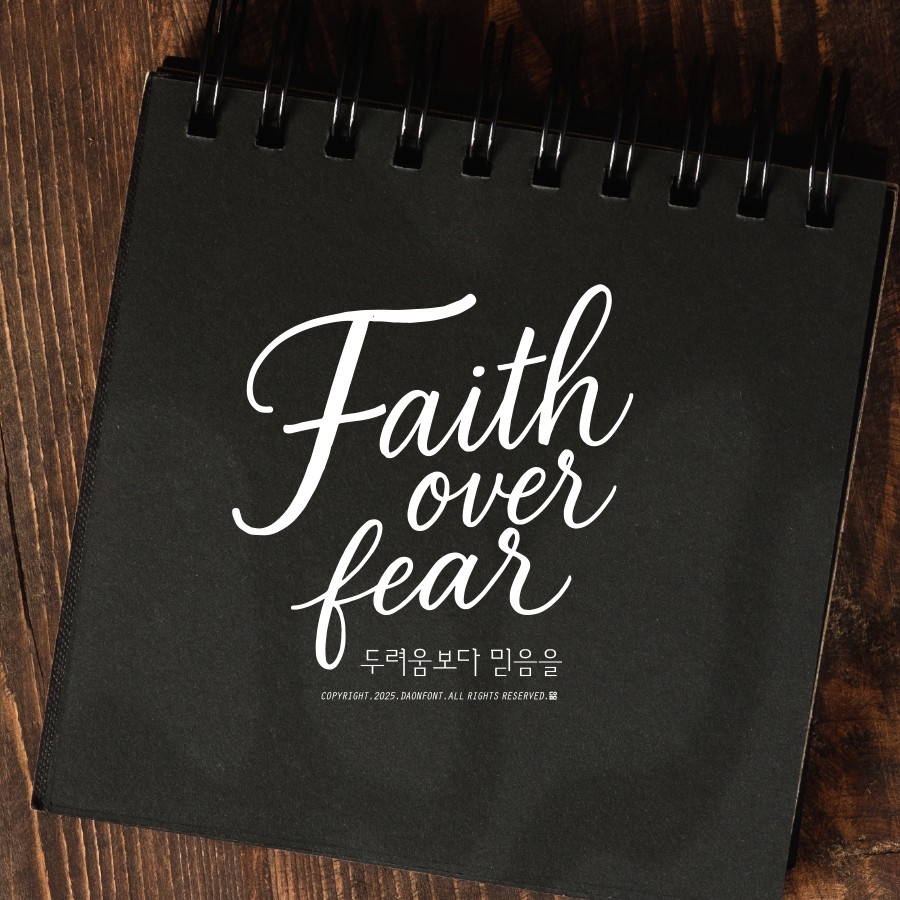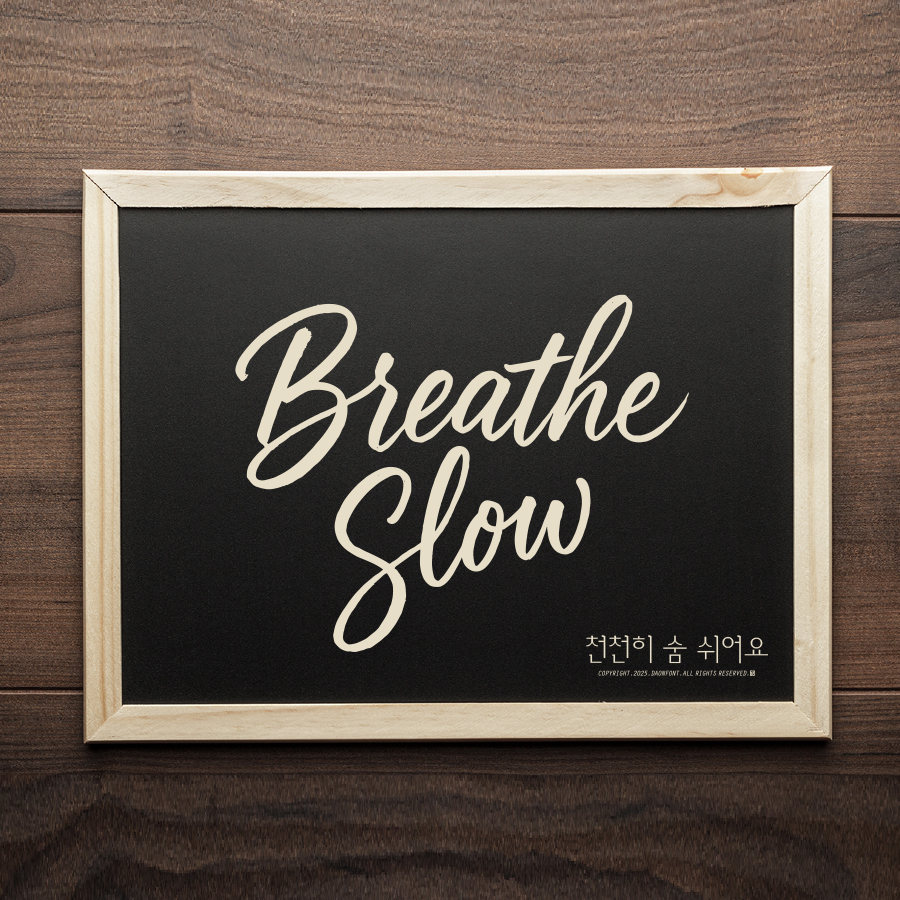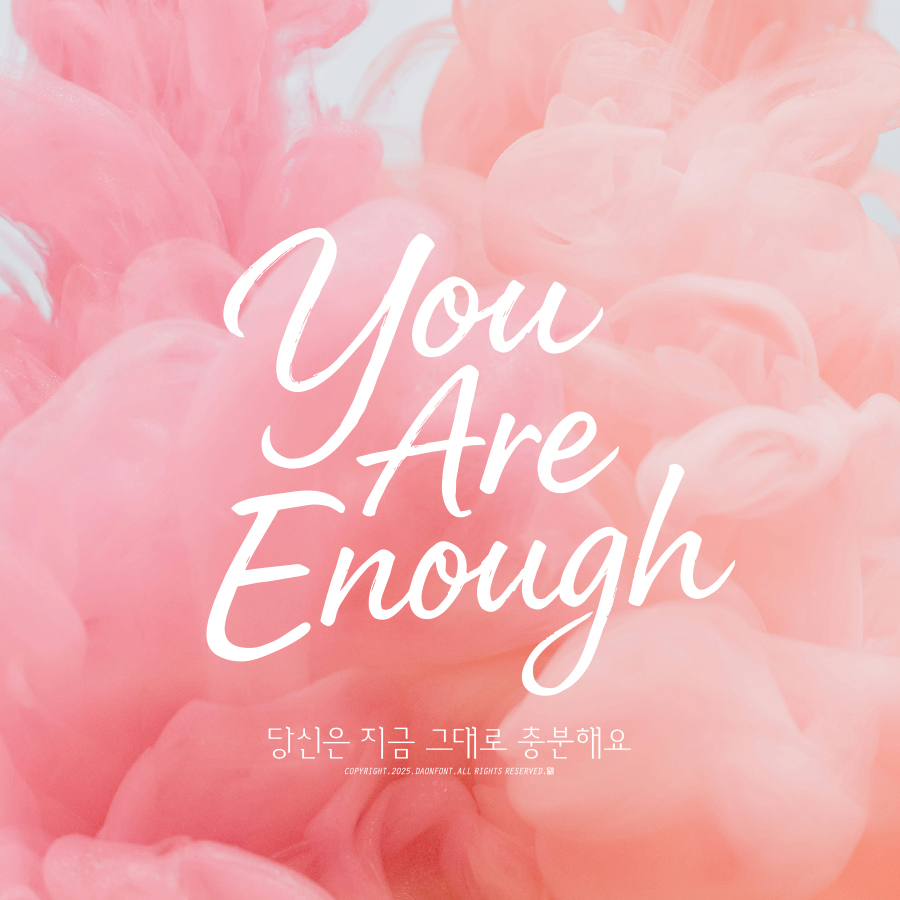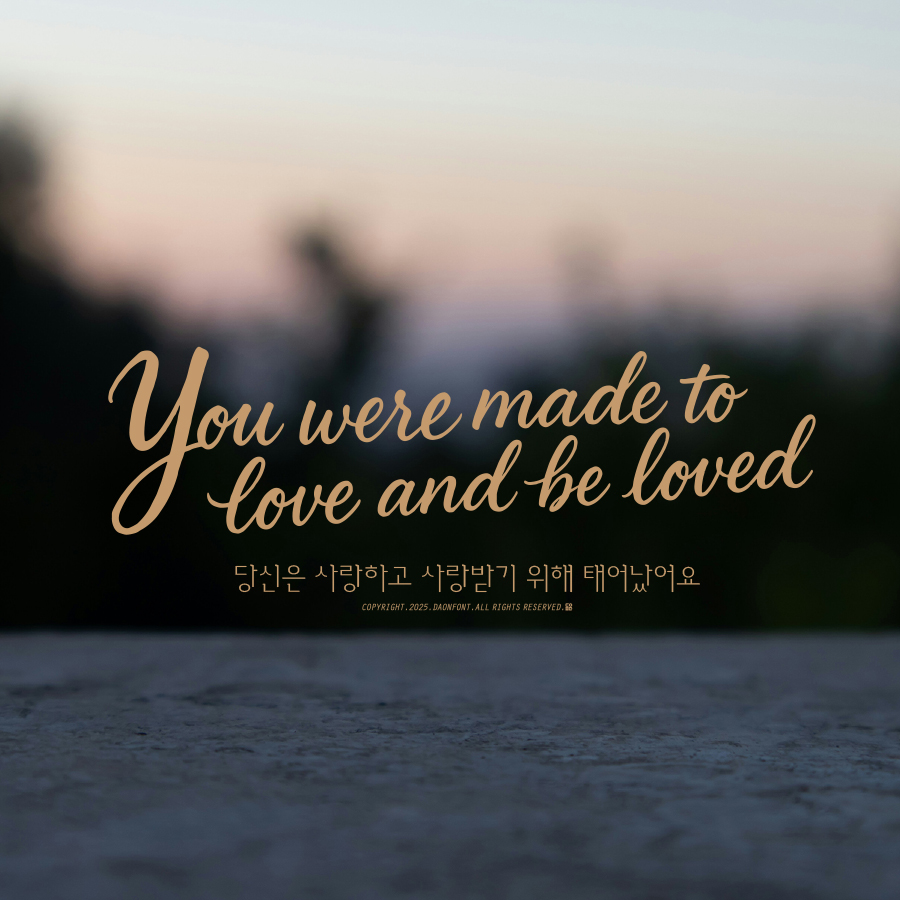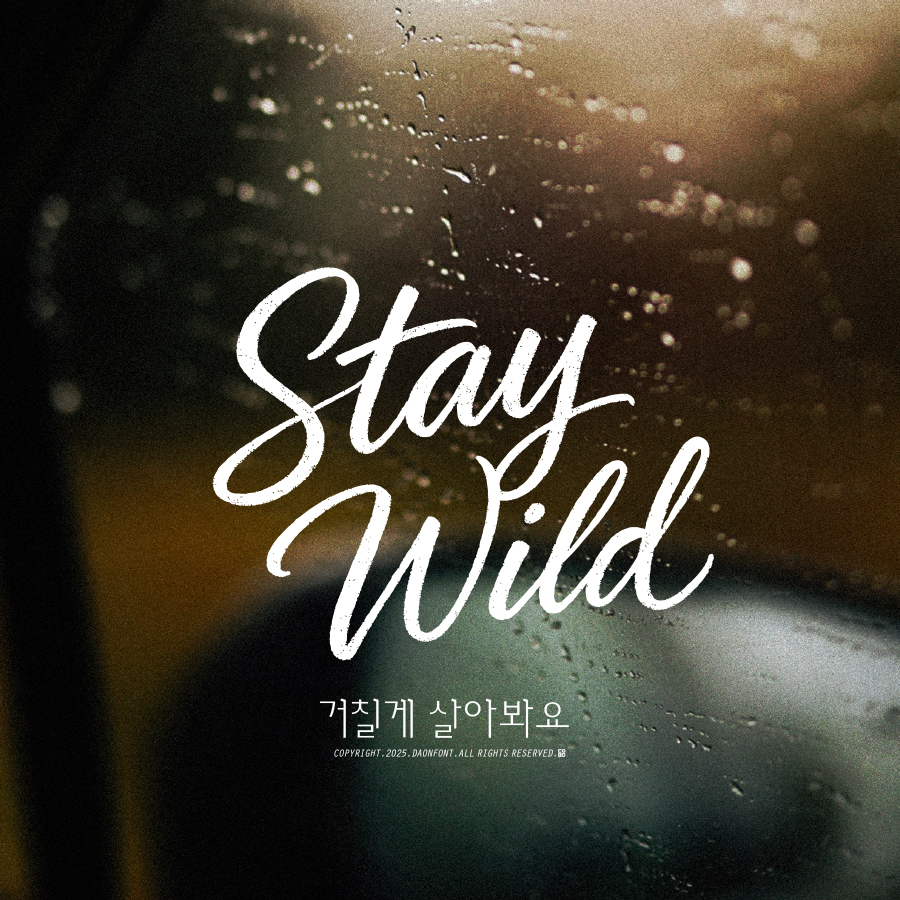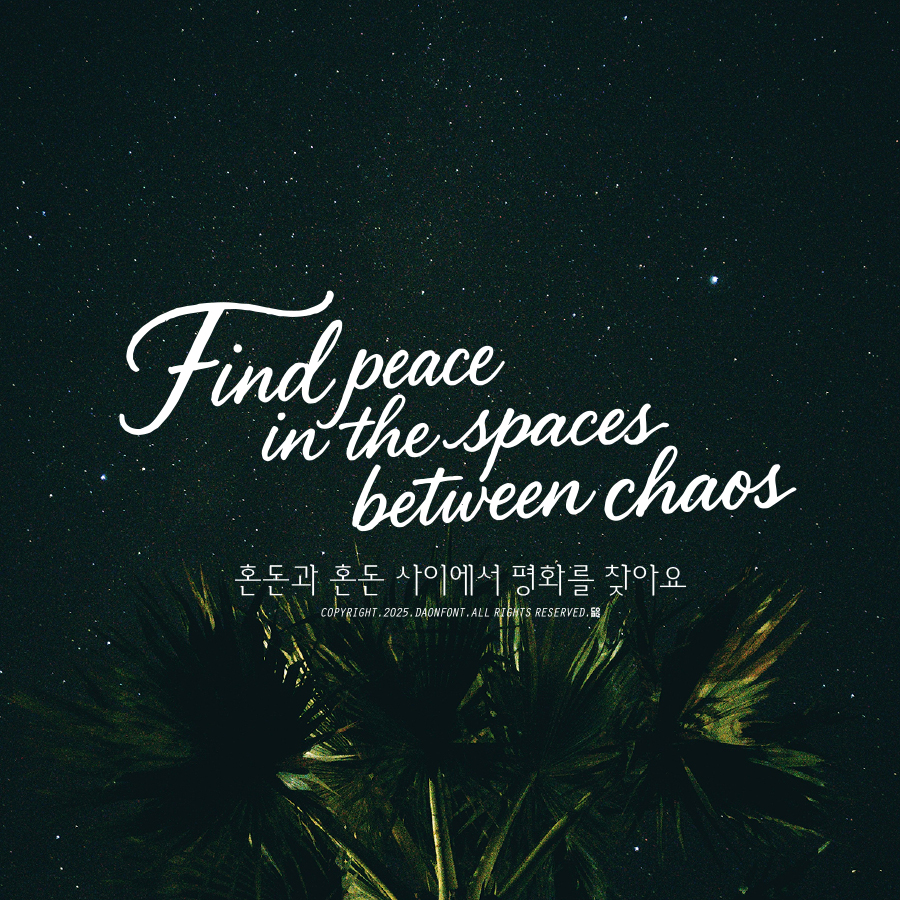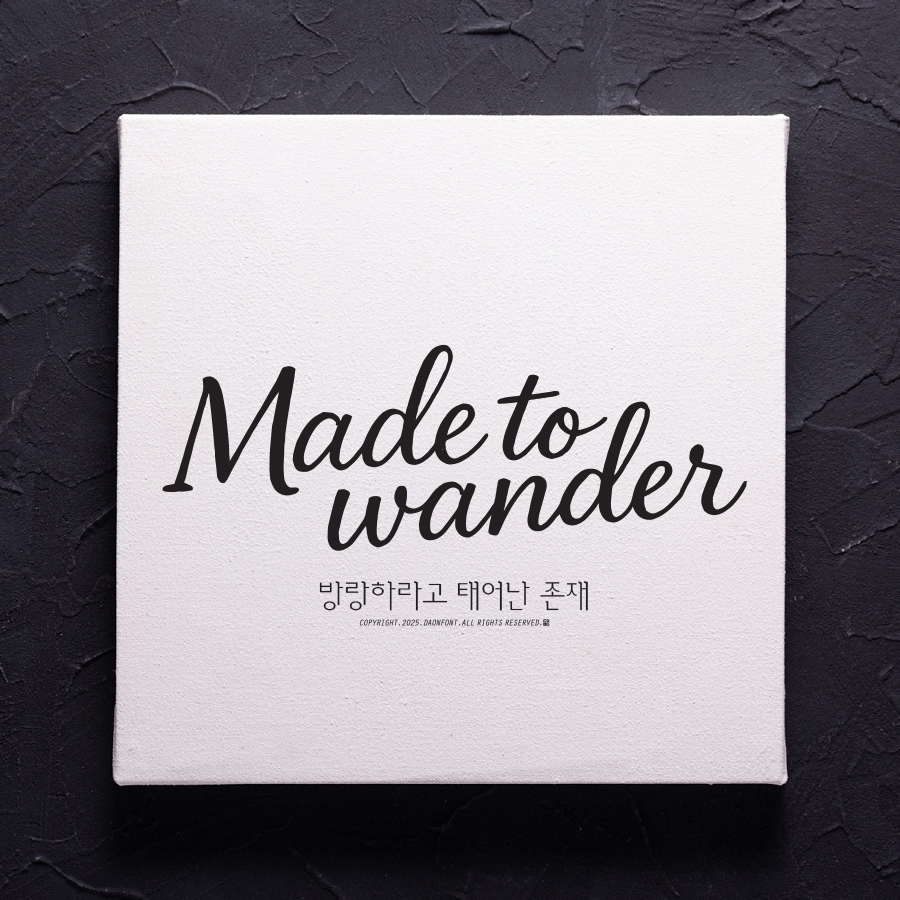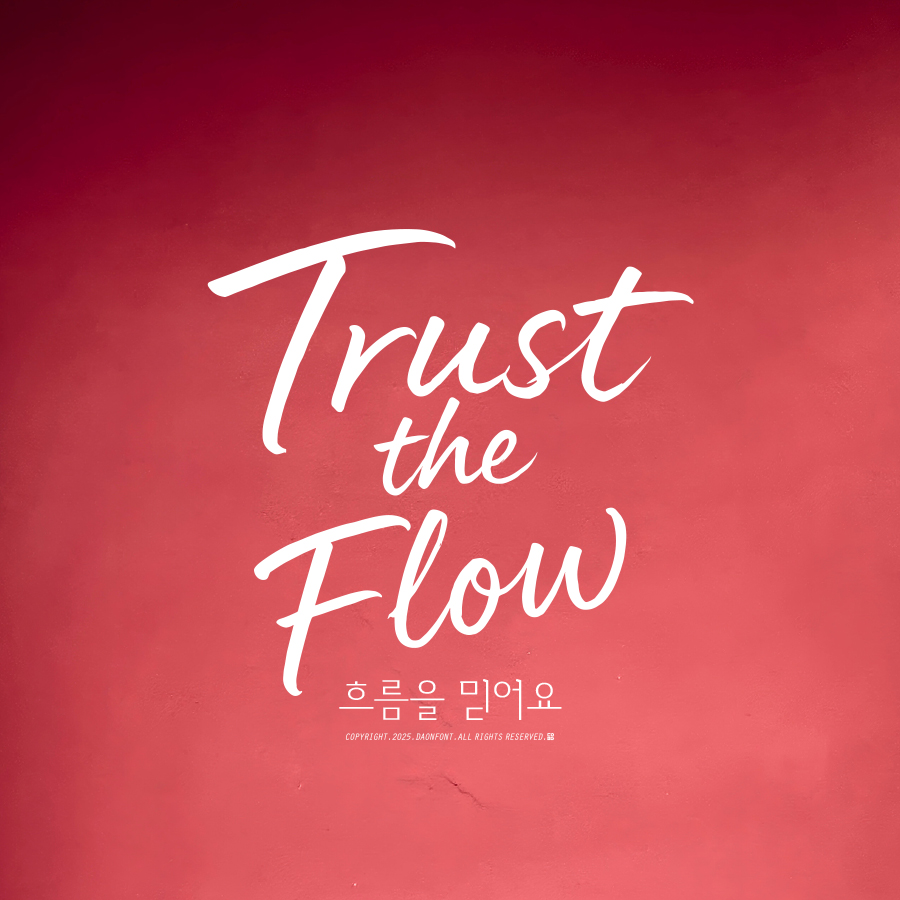
다온폰트 영문캘리그라피 서비스 개시
다온폰트 캘리전용서비스에 영문 캘리그라피 신청이 가능해졌습니다.
다온폰트의 캘리전용서비스에서 이제 영문 텍스트도 감도 높은 캘리그라피로 제작해드립니다.
폰트가 아닌, 벡터 기반 캘리그라피로 제공되며 문구의 길이나 분위기에 따라 조형이 유동적으로 구성됩니다.
디자인에 필요한 감정, 이젠 언어를 넘어 함께합니다.